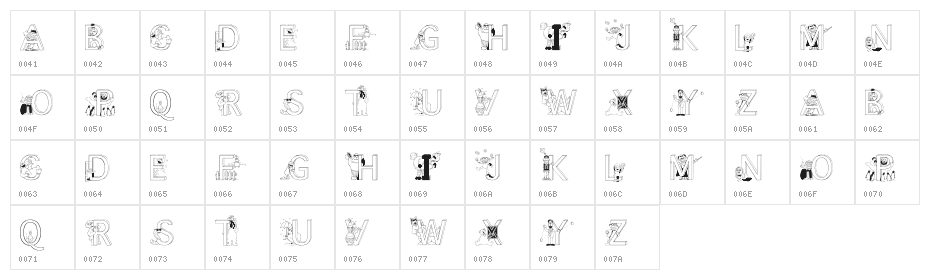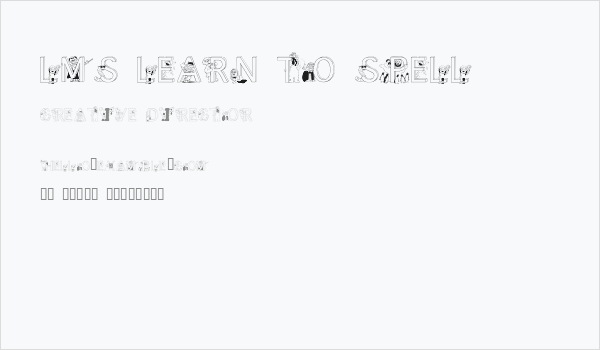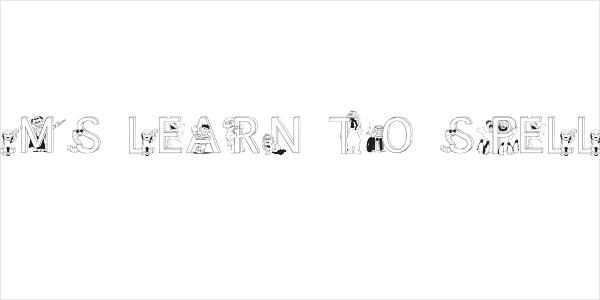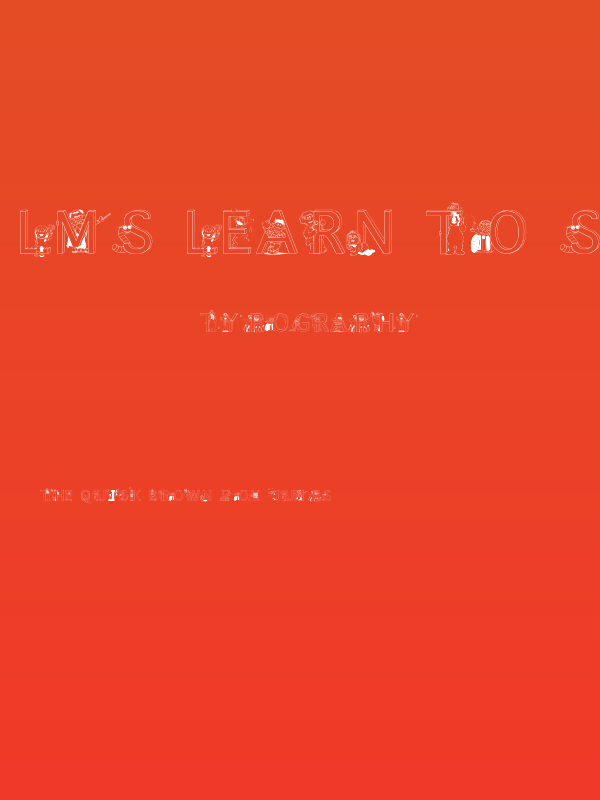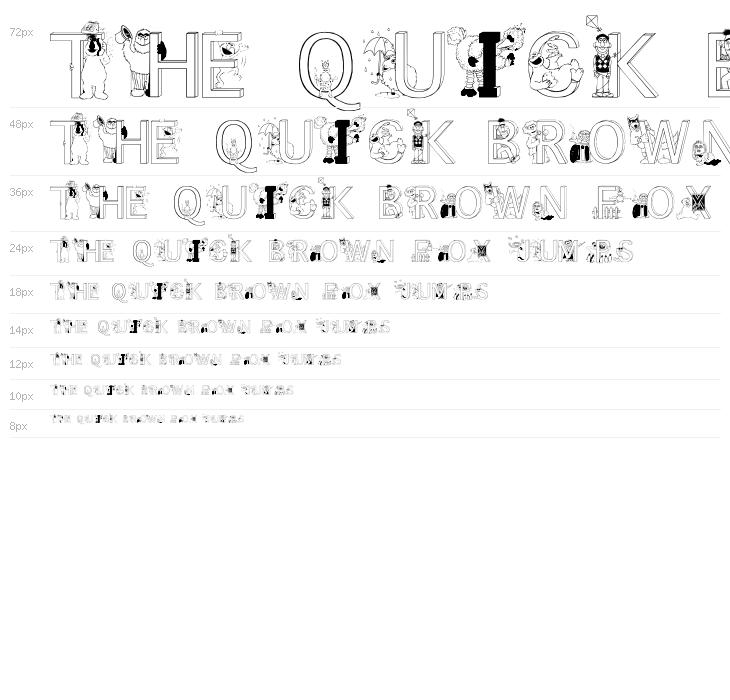
LMS Learn To Spell Font
| Stile generale | Playful, Whimsical, Decorative |
| Caso d'uso | Headlines, Logos, Educational materials |
| Progetti proposti | Ideal for children's books, educational posters, playful branding, and creative invitations. |